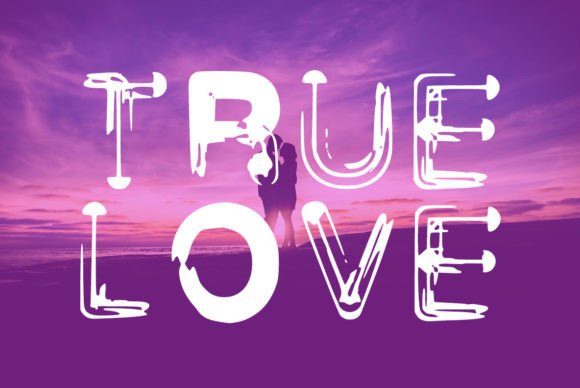
SVG Font Bundle Wet Brush
適切なデザイン要素を見つけるのは難しい場合がありますが、SVG Font Bundle Wet Brushは作品を即座に引き立てる優れたコレクションを提供します。
POD(オンデマンド印刷)製品、結婚式の招待状、またはソーシャルメディアのグラフィックを作成している場合でも、SVG Font Bundle Wet Brushは理想的です。